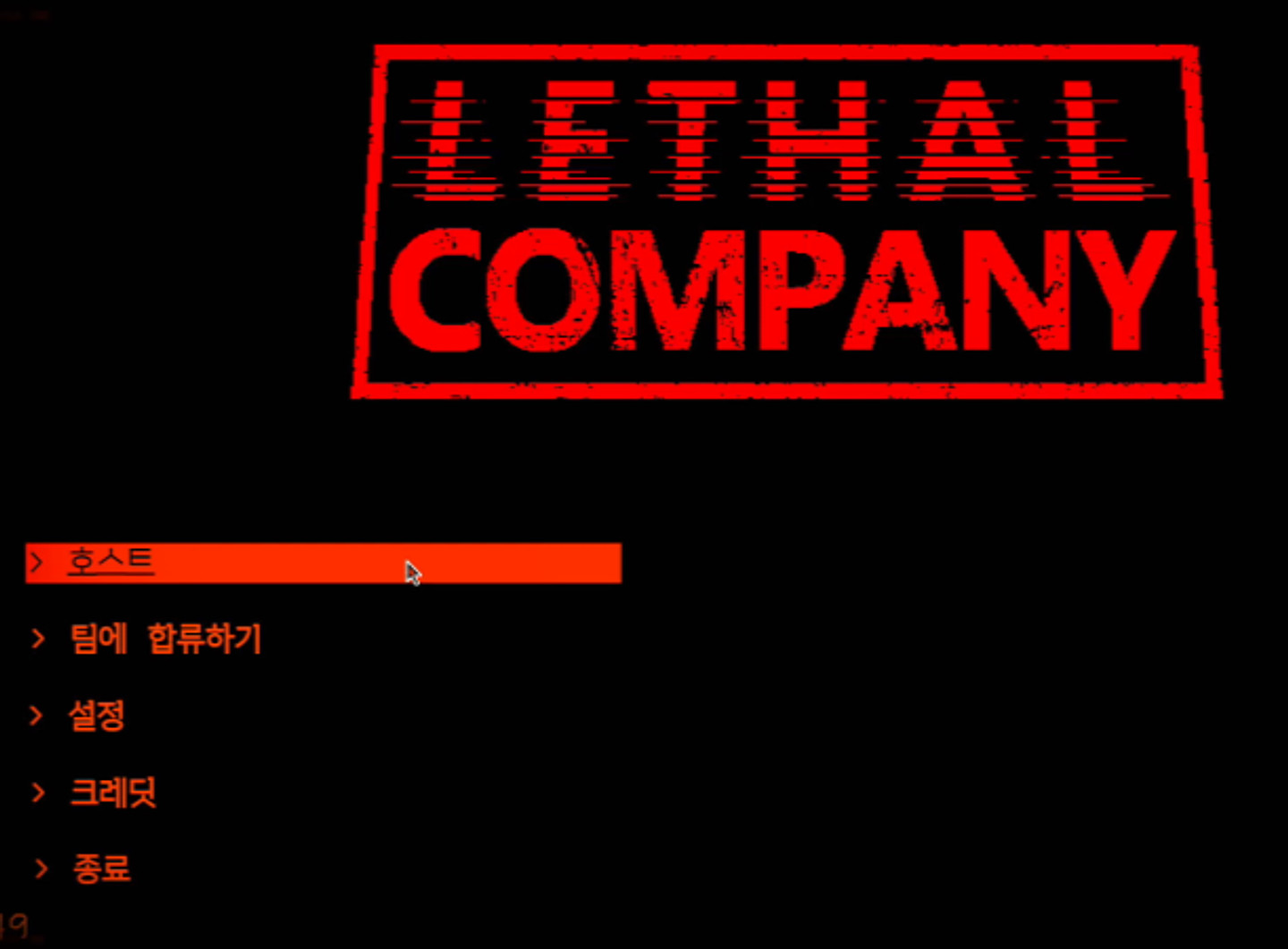
리썰컴퍼니 로고랑 비슷한 폰트 있을까요?
산세리프
기본 산세리프 효과에 글리치(상단)/노이즈(하단) 효과를 적용한 것 같습니다. 포토샵을 다루실 줄 아시면 Futura 같은 기본 산세리프 폰트에 직접 적용하시면 좋을 것 같고 비슷한 효과의 폰트를 원하신다면 상단은 Pixter Glitch Bold (유료) 하단은 Single Bound Vintage Bold (유료) 가 유사해보입니다. 무료 폰트를 찾으신다면 dafont에서 상단은 glitch 키워드로 찾아보시고 하단은 eroded 키워드로 찾아보세요!